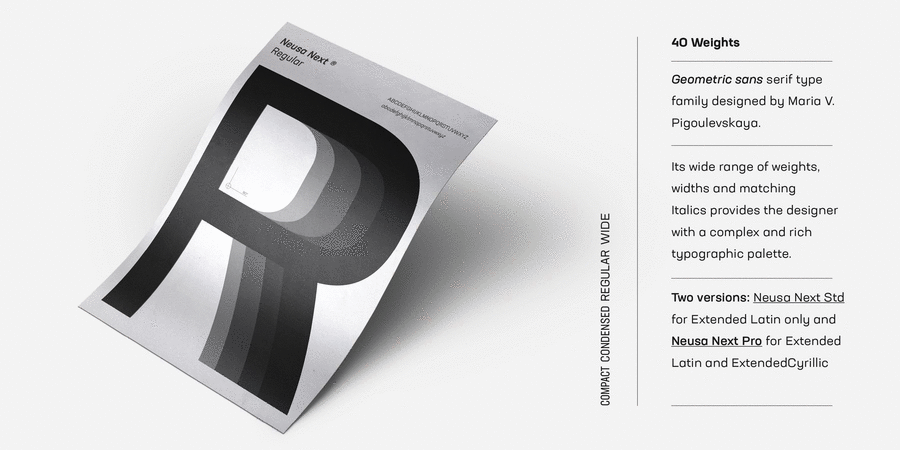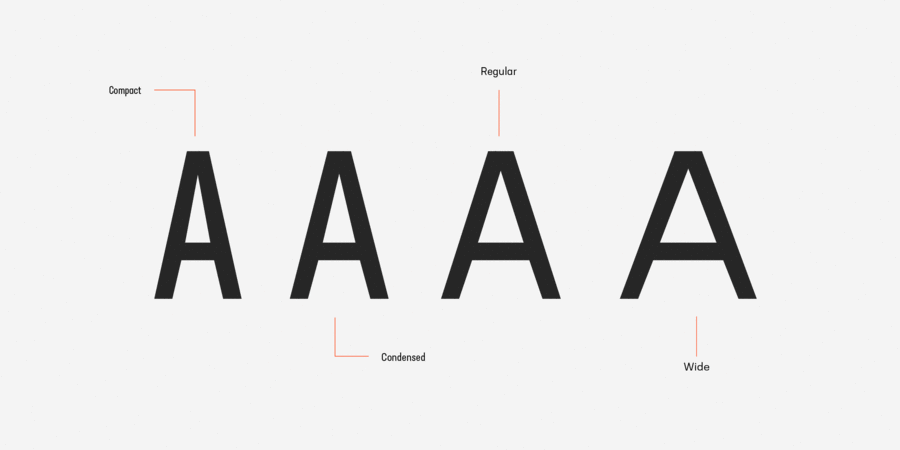
Neusa Next Pro – це сімейство геометричних гротесків з широким діапазоном насиченості й ширини. Гарнітура надає дизайнерові складну й багату типографічну палітру. Розроблений та випущений як Neusa в 2012 році, проект задумувався як компактне шрифтовое сімейство. Прийнятний для тексту, шрифт мав відмітні характеристики, які дозволяли йому також працювати в акціденціі. Сьогодні Neusa Next Pro розширює набір символів до розширеної кирилиці та включає ще три ширини: вузьку, звичайну та широку, кожен з наборів накреслень має свій індивідуальний характер. На такий дизайн надихнули ранні дослідження космосу, в тому числі культова обкладинка журналу «Life» 1969 на тему програми Apollo та, звичайно, твори швейцарських дизайнерів. Сімейство Neusa Next Pro складається з 20 ваг, по п'ять жирностей на кожну ширину, з відповідними курсивами, всього 40 накреслень. Можливості OpenType включають локалізовані форми для башкирської, болгарської, каталонської, чуваської, голландської, македонської, молдавської, румунської та сербської мов, а також верхні й нижні дроби, пунктуацію з урахуванням регістру та спеціальний стилістичний набір з іконками космічної тематики. Мовна підтримка включає латинські та кириличні алфавіти більшості західноєвропейських і центральноєвропейських мов, заснованих на латинці. Шрифт розробила Марія Пігулевська у 2017 році. Neusa Pro™ є торговою маркою компанії The Northern Block.
Асоціації з сімейством шрифтів Neusa Next ProОсобистість і характер гарнітури:
точний, рівний, прямокутний, стійкий, статичний, міський, прозорий, тонкий, холодний, скляний, крихкий, дротяний, вузький, високий, стрункий, худий, гладенький, якісний, розумний, стабільний, техногенний, урбаністичний, переконливий, твердий, серйозний, надійний, впевнений, сильний, індустріальний, авторитетний, автоматичний, сталевий, міцний, формальний, діловий, сучасний, монотонний, логічний, прагматичний, практичний, штучний, машинний, інженерний, мотивуючий, крутий, залізничний, креслярський, космічний, футуристичний, архітектурний, робочий, відповідальний, важливий, військовий, важкий, залізний, амбітний, гучний, строковий, мінімалістичний, лаконічний, Простий, модний, західний, спокійний, легкий, ясний, чистий, невагомий, неоновий, динамічний, глобалізований, глобалістічний, технічний, спортивний, солідний, значний, швидкий, рішучий, гоночний, швидкісний, мужній, потужний, помітний, гострий, чіткий, різкий, дзвінкий, яскравий, масивний, громіздкий, жорсткий, щільний, суворий
техніка, прилад, архітектура, наука, дизайн, Місто, технології, верстат, інструмент, урбаністика, завод, інженер, автоматика, інститут, космос, новини, промисловість, електростанція, енергетика, хмарочос, машинобудування, порт, конструктор, будівництво, вагон, креслення, залізниця, гаджет, девайс, айтішник, айті, IT, архітектор, робочий, кінотеатр, цигарки, тренажери, ремонт, ракета, супутник, армія, зброя, страйкбол, Футбол, спорт, кіберспорт, комп'ютерна гра, селфі, астрономія, мотор, двигун, вантажівка, далекобійник, авіація, літак, Локдаун, чистота, гігієна, шампунь, інтернет, мобільний зв'язок, бізнес, транспорт, аеропорт, метро, ліки, медицина, фінанси, фантастика, вода, хімія, фізика, авто, автомобіль, автобус, паливо, залізо, комп'ютер, блокбастер, бойовик, екшен, логістика, швидкість, ралі, Доставка, телебачення, металургія, нафта, гонки Гарнітура має ознаки стилів: